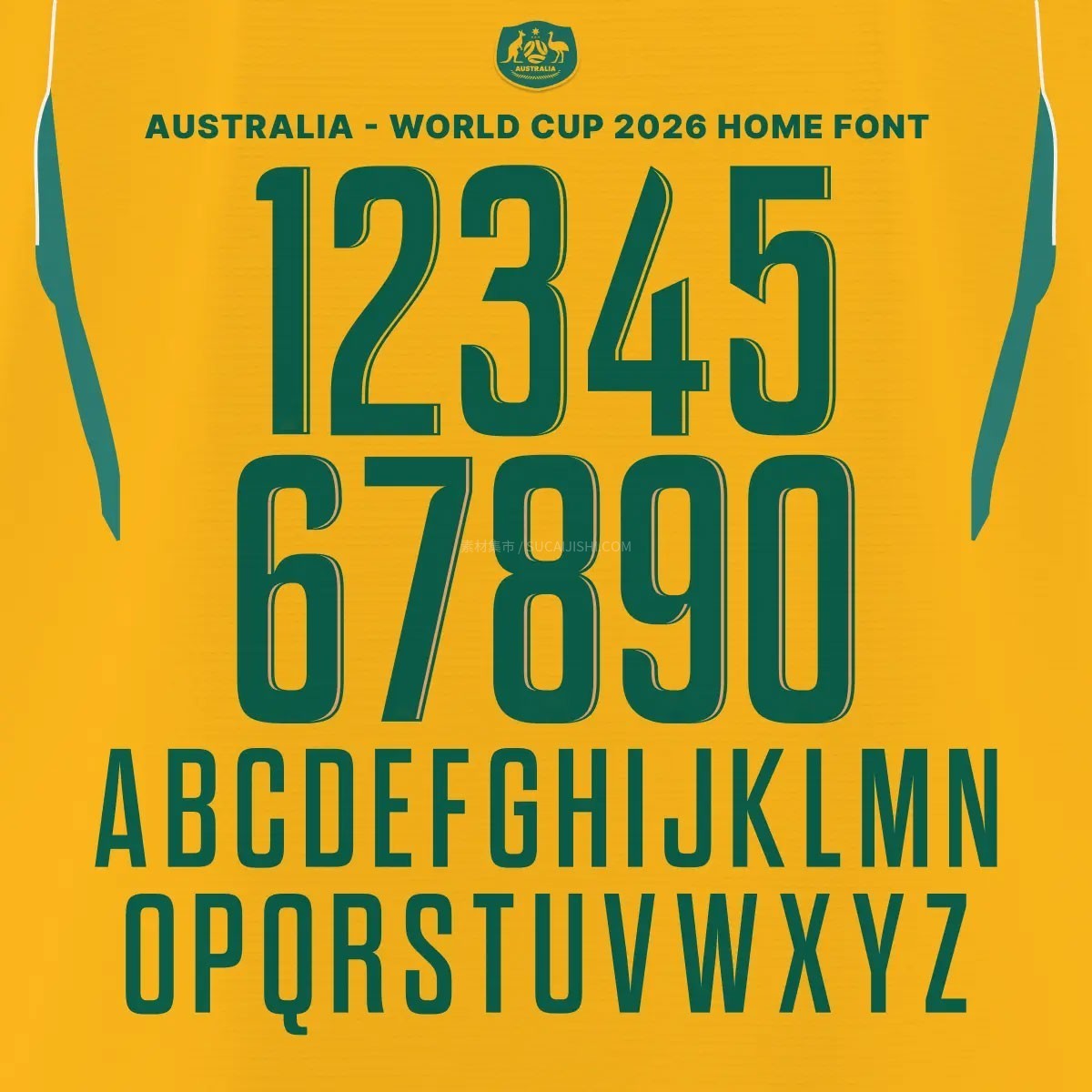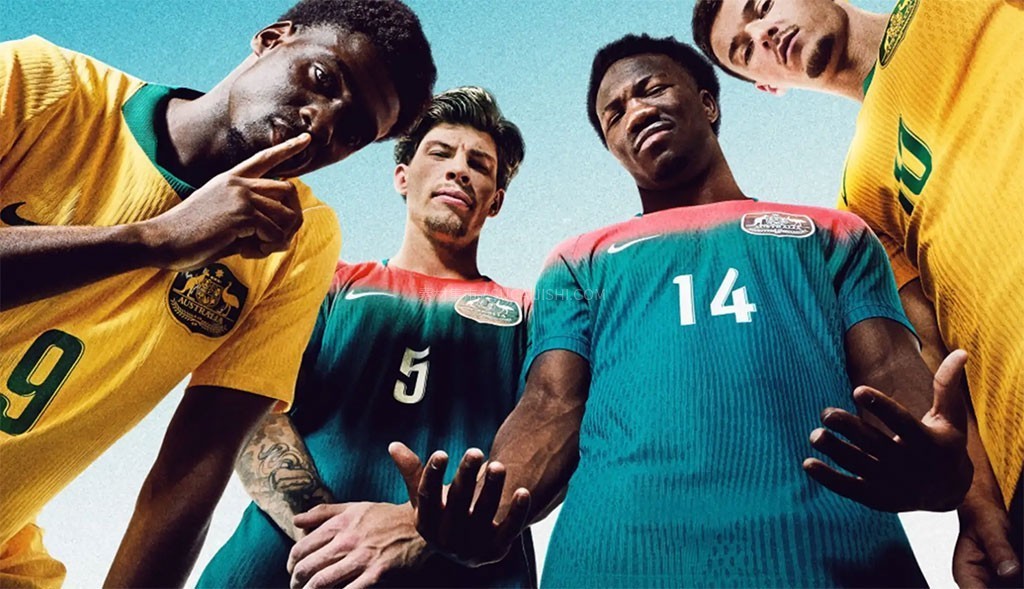
澳大利亚2026年世界杯主场球衣字体
这套澳大利亚 2026 世界杯主场专属字体,完美捕捉了“标志性澳大利亚”的活力与激情!它不仅是助力澳大利亚国家队(Socceroos)连续第六次征战世界杯的视觉核心,更是对 2006 年传奇球衣和经典 Total 90 时代的一波完美致敬。字体采用了极具辨识度的醒目几何图形设计,并融入了耐克 Aero-FIT 的创新感。无论你是做赛事海报、球衣印制还是运动风排版,这款融合了复古经典与未来乐观主义的字体,都能让你的作品瞬间充满竞技力量!